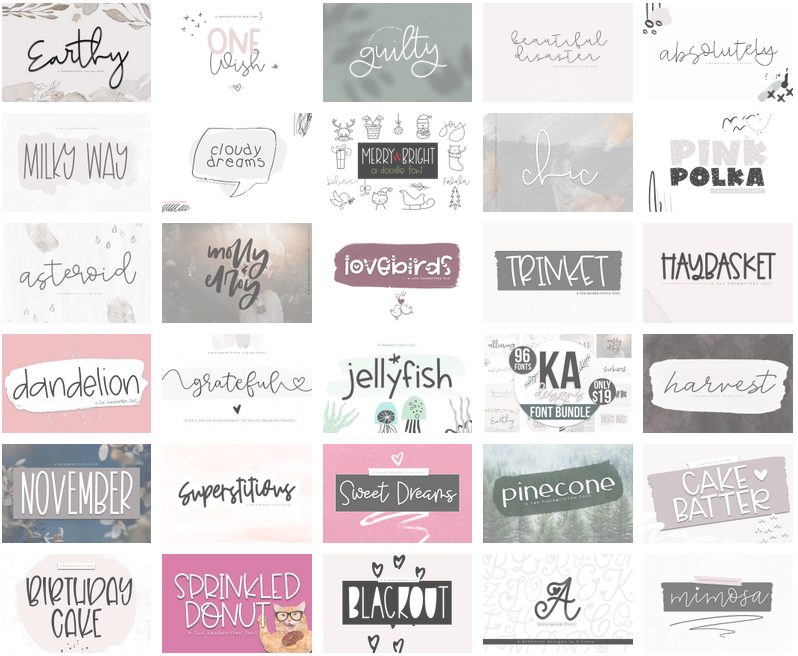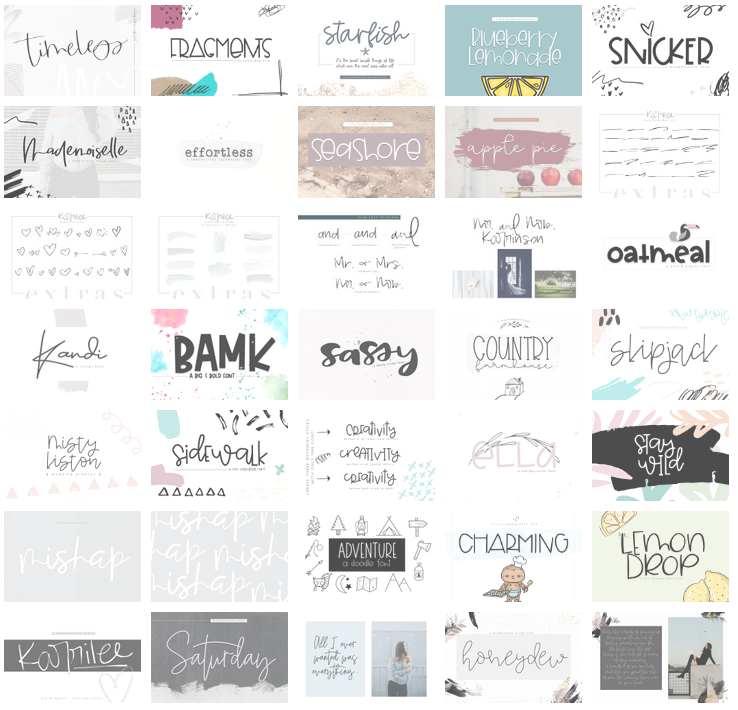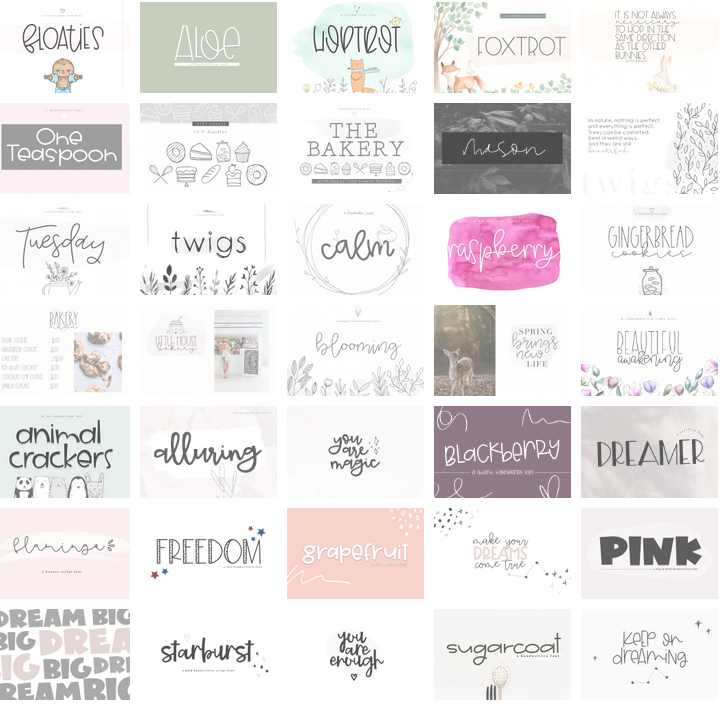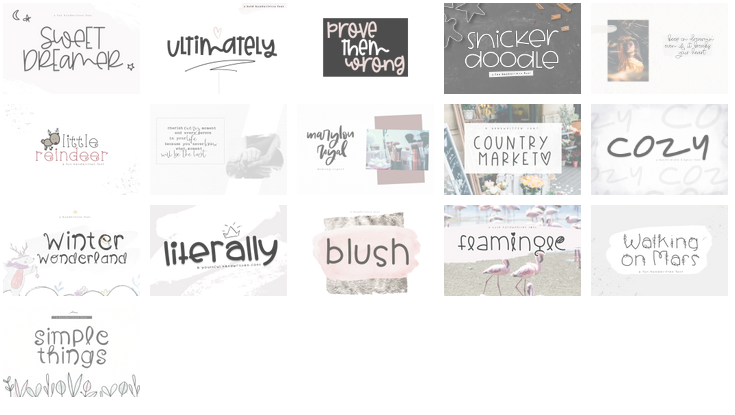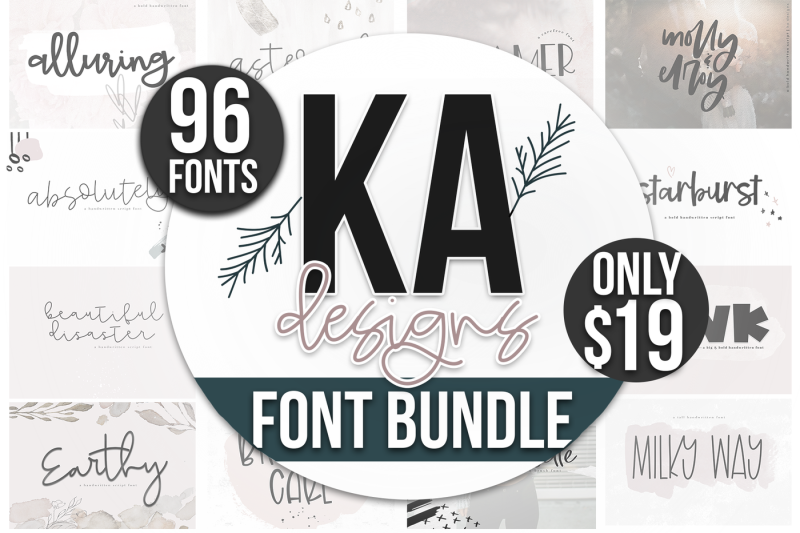
Best of 2018 BIG Font Bundle – Bộ sưu tập Font của KA Designs
**Best of 2018 BIG Font Bundle – Bộ sưu tập Font của KA Designs: Nâng tầm sáng tạo cho người dùng Mac!** ✨
Chào mừng bạn đến với “Best of 2018 BIG Font Bundle” – Tuyệt phẩm font chữ độc đáo từ KA Designs, được tuyển chọn đặc biệt dành cho những nhà sáng tạo cá nhân trên MacBook! 🎨 Bộ sưu tập này mang đến một kho tàng 50 font chữ viết tay ấn tượng, đa dạng phong cách từ retro, ngọt ngào đến hiện đại, giúp mọi dự án thiết kế của bạn trở nên sống động và thu hút hơn bao giờ hết. 💖
1. Molly & Elroy [OTF & TTF]
2. Lovebirds [OTF & TTF]
3. Starburst [OTF & TTF]
4. Beautiful Disaster [OTF & TTF]
5. Absolutely [OTF & TTF]
6. Guilty [OTF & TTF]
7. Country Market [OTF & TTF]
8. Blackberry [OTF & TTF]
9. Gingerbread Cookies Font Duo [OTF & TTF]
10. Sugar & Nutmeg [OTF & TTF]
11. Sugarcoat [OTF & TTF]
12. Milky Way [OTF & TTF]
13. Birthday Cake [OTF & TTF]
14. Honeydew [OTF & TTF]
15. Snickerdoodle [OTF & TTF]
16. Sprinkled Donut [OTF & TTF]
17. Snicker [OTF & TTF]
18. Mimosa [OTF & TTF]
19. Apple Pie [OTF & TTF]
20. Oatmeal [OTF & TTF]
21. Grapefruit [OTF & TTF]
22. Dreamer [OTF & TTF]
23. Mishap [OTF & TTF]
24. Sweet Dreamer [OTF & TTF]
25. Superstitious [OTF & TTF]
26. Chic [OTF & TTF]
27. Earthy [OTF & TTF]
28. Asteroid [OTF & TTF]
29. Alluring [OTF & TTF]
30. Alluring Extras [OTF]
31. Merry & Bright Doodle Font [TTF]
32. Winter Doodle Font [TTF]
33. Adventure Doodle Font [TTF]
34. Little Reindeer [OTF & TTF]
35. Beautiful Awakening Font Duo [OTF & TTF]
36. Sidewalk [OTF & TTF]
37. Skipjack [OTF & TTF]
38. Ultimately [OTF & TTF]
39. Pink Polka [OTF & TTF]
40. Pink [OTF & TTF]
41. Blooming [OTF & TTF]
42. Freedom [OTF & TTF]
43. Timeless [OTF & TTF]
44. Flamingo [OTF & TTF]
45. Cloudy Dreams [OTF & TTF]
46. Trinket [OTF & TTF]
47. Haybasket [OTF & TTF]
48. Grateful [OTF & TTF]
49. Cozy [OTF & TTF]
50. Flamingle [OTF & TTF]
51. Fragments [OTF & TTF]
52. Blueberry Lemonade [OTF & TTF]
53. Starfish [OTF & TTF]
54. Seashore [OTF & TTF]
55. Effortless [OTF & TTF]
56. Simple Things [OTF & TTF]
57. Jingle Bells [OTF & TTF]
58. Jellyfish [OTF & TTF]
59. Walking on Mars [OTF & TTF]
60. Handwrite [OTF & TTF]
61. November [OTF & TTF]
62. Harvest [OTF & TTF]
63. Raspberry [OTF & TTF]
64. Calm [OTF & TTF]
65. The Bakery [OTF & TTF]
66. Animal thuocers [OTF & TTF]
67. Blush [OTF & TTF]
68. Iced Coffee [OTF & TTF]
69. Literally [OTF & TTF]
70. Dandelion [OTF & TTF]
71. Winter Wonderland [OTF & TTF]
72. Sweet Dreams [OTF & TTF]
73. Karrilee [OTF & TTF]
74. Lemon Drop [OTF & TTF]
75. Charming [OTF & TTF]
76. Floaties [OTF & TTF]
77. Pinecone [OTF & TTF]
78. For the Gram Monogram [OTF & TTF]
79. Blackout [OTF & TTF]
80. BAMK [OTF & TTF]
81. Mademoiselle [OTF & TTF]
82. Kandi [OTF & TTF]
83. Country Farmhouse [OTF & TTF]
84. Sophisticated [OTF & TTF]
85. Ella [OTF & TTF]
86. Sassy [OTF & TTF]
87. Tuesday [OTF & TTF]
88. Saturday [OTF & TTF]
89. Aloe [OTF & TTF]
90. Mason [OTF & TTF]
91. Twigs [OTF & TTF]
92. One Teaspoon [OTF & TTF]